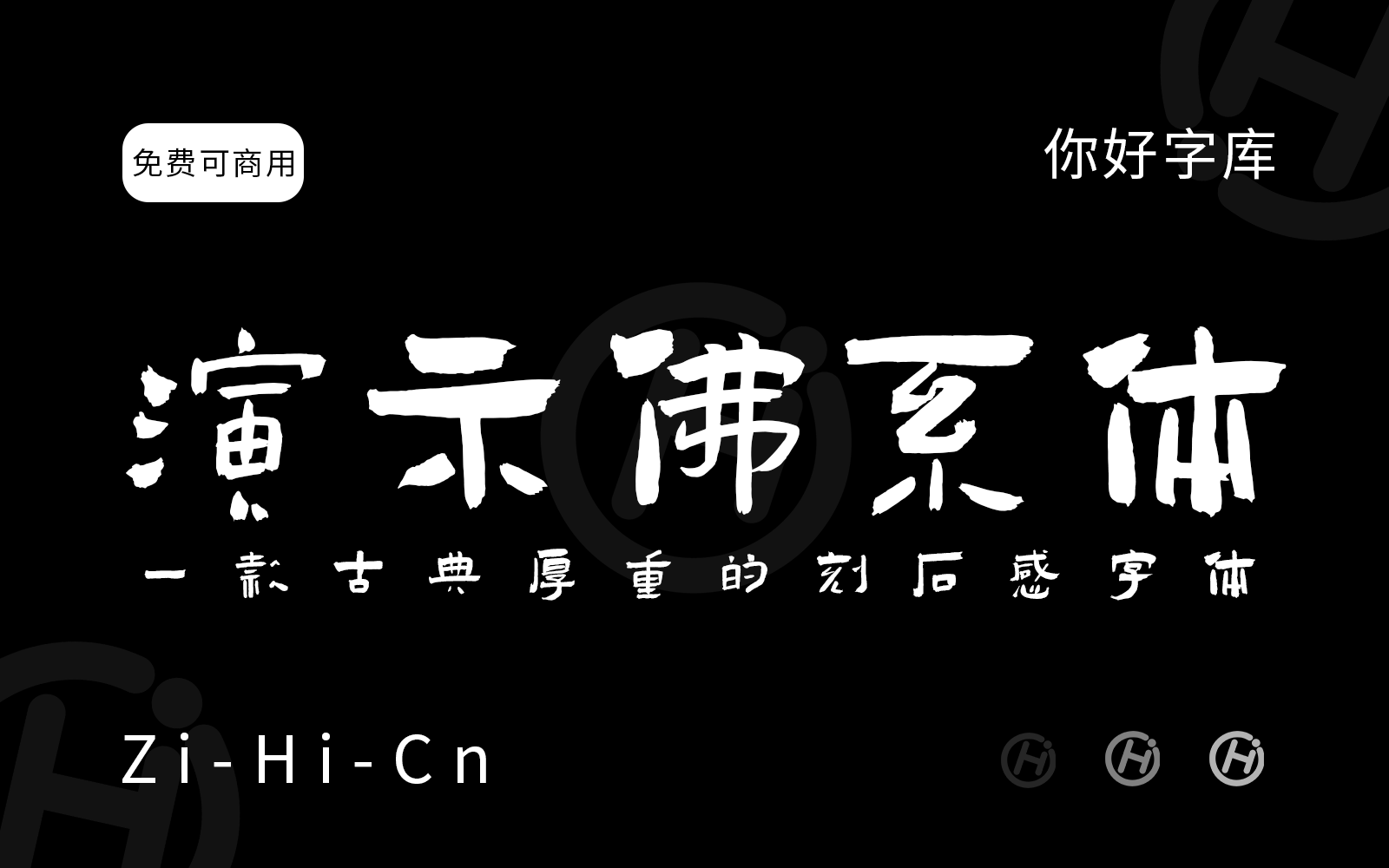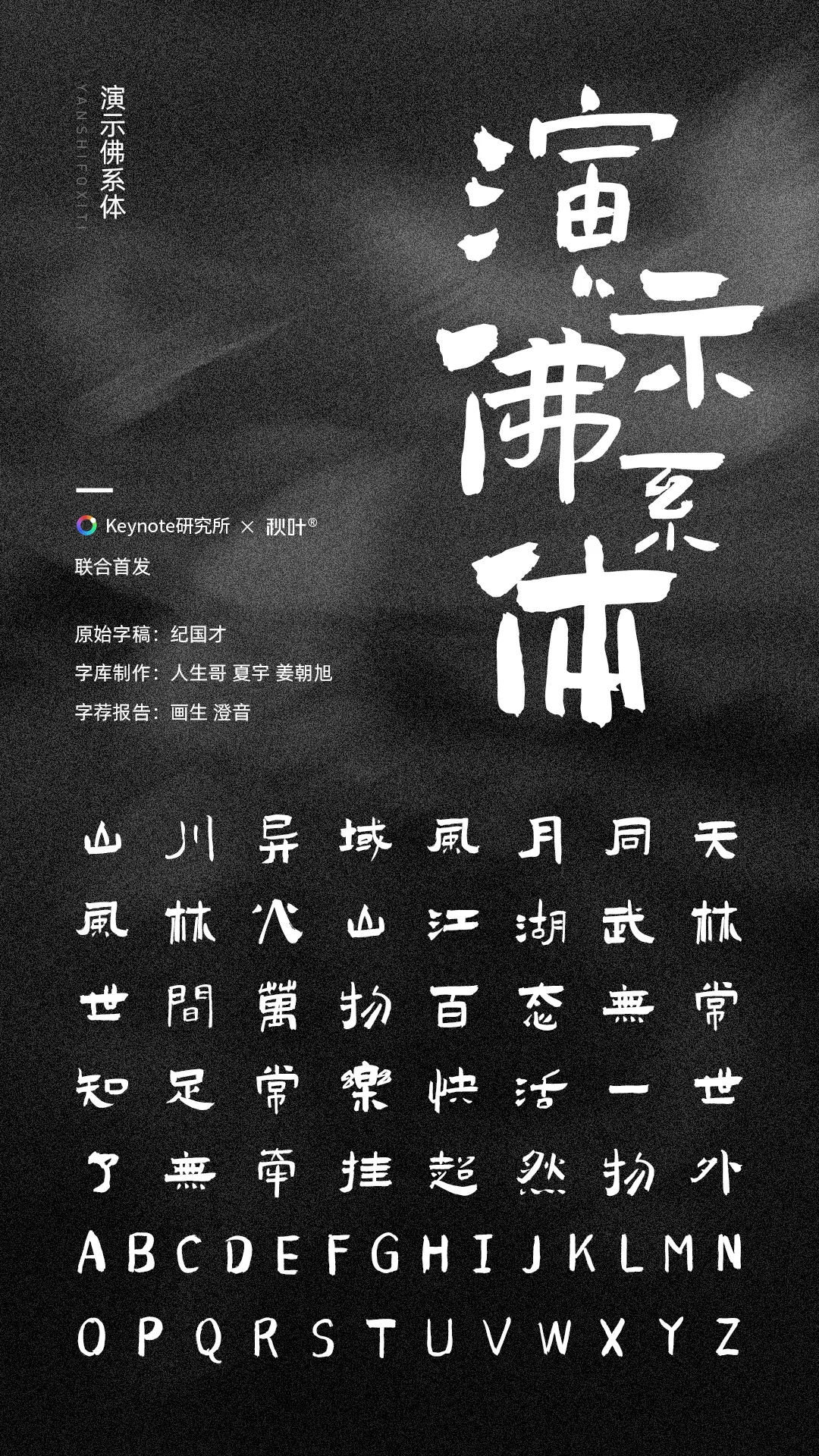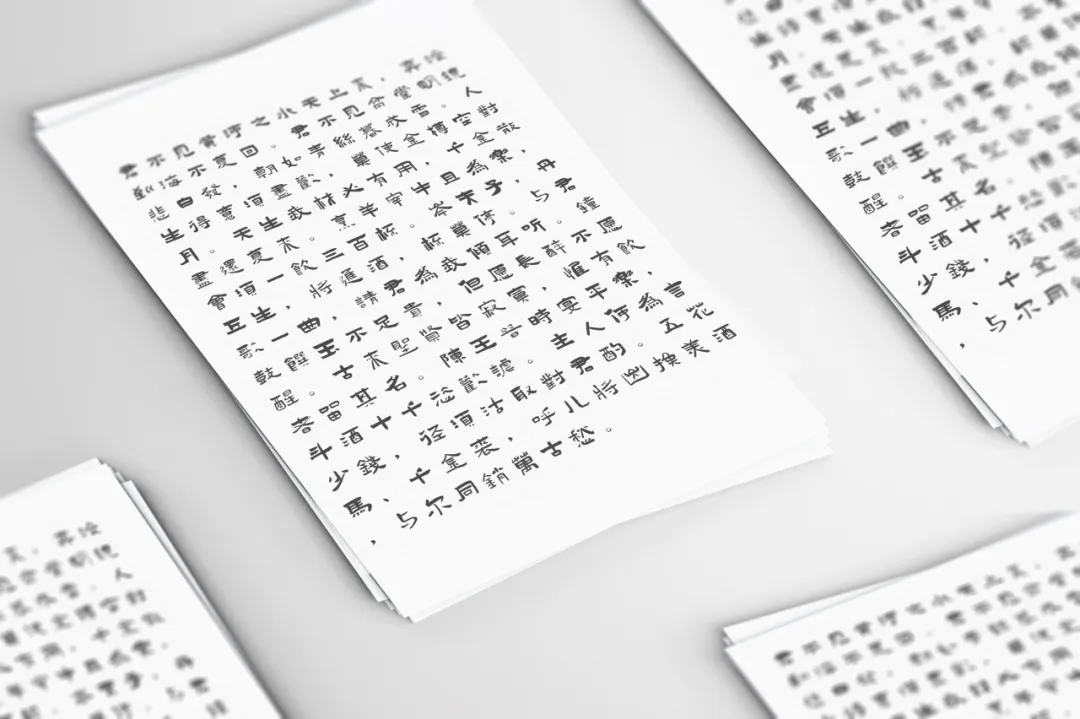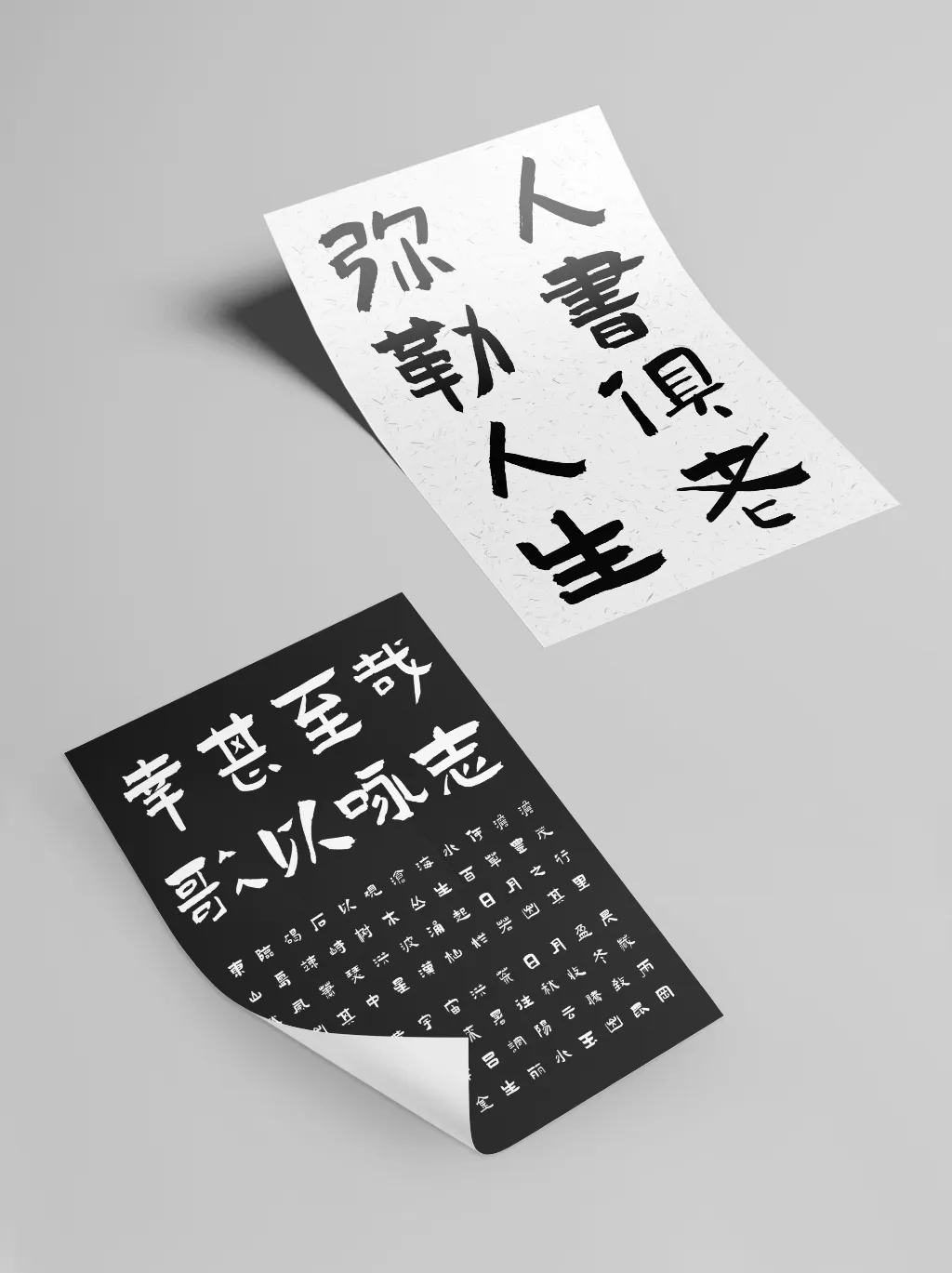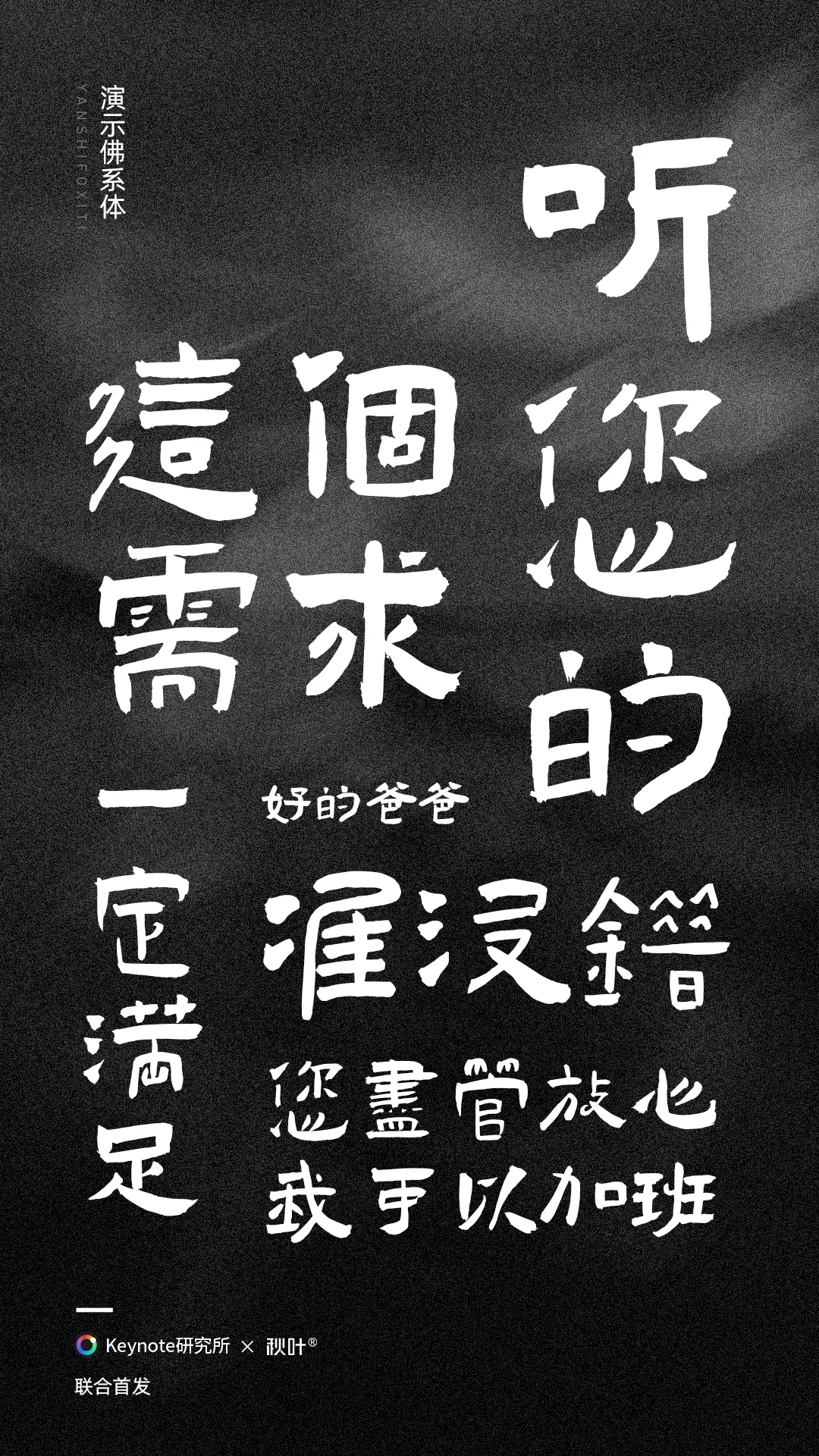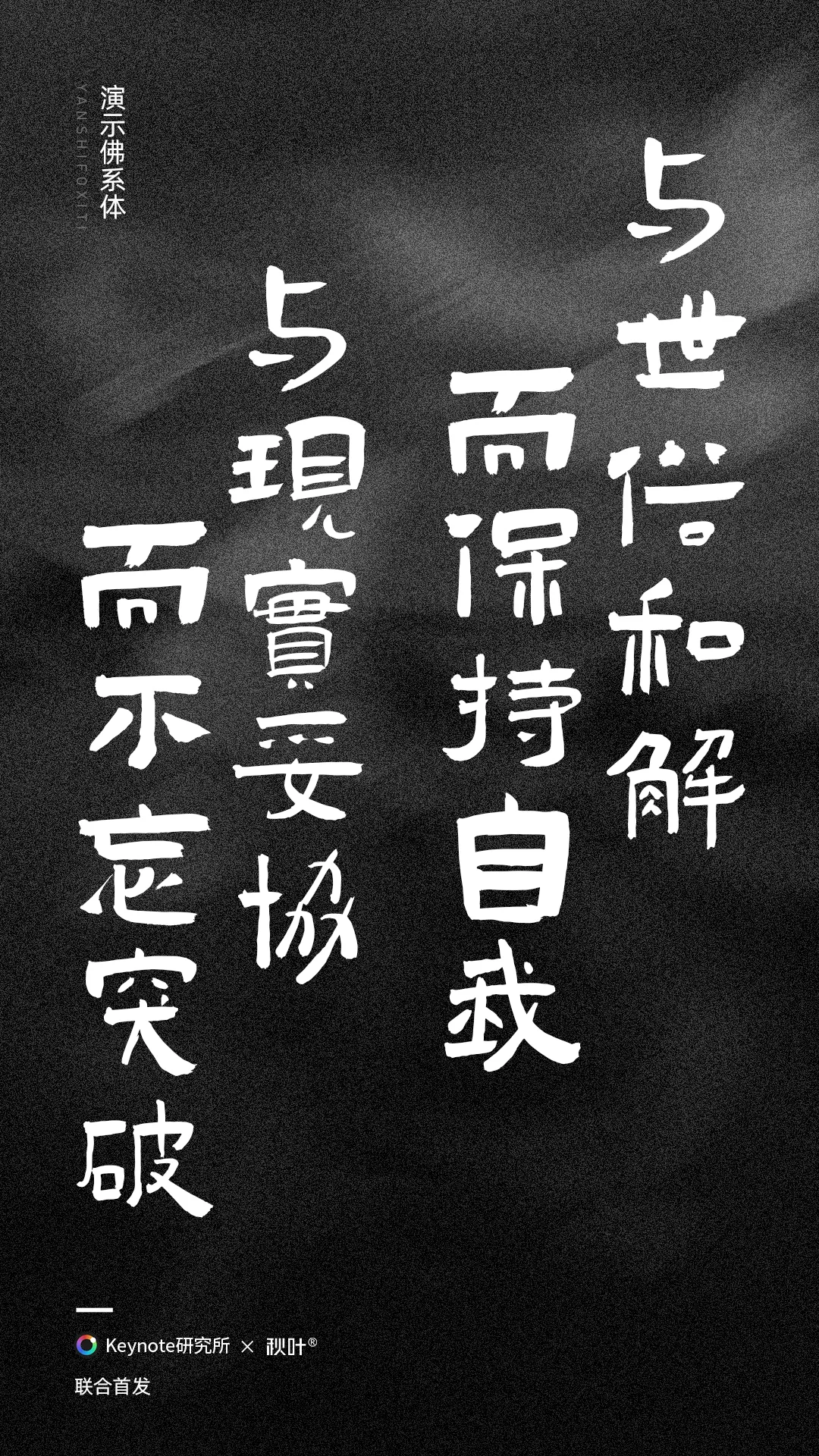
演示佛系体
字体简介
“演示佛系体”是一款由80岁书法家纪国才创作的免费中文字体,于2020年3月由Keynote研究所和秋叶PPT联合首发。它属于书法风格,灵感源自小篆,笔画独立分明,没有传统书法字体的连笔或轻重变化,呈现出古典厚重的刻石感。字体包含6953个字符,覆盖GB2312标准的6763个汉字,支持简体中文、基本拉丁文和符号,适合海报、标题或文化设计。